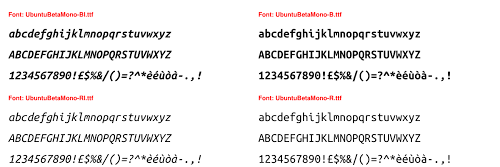
Ubuntu Font Family: Arriva il Font Ubuntu Monospace beta! Ecco come installarli su Ubuntu
Novità in casa Canonical, da pochi giorni è disponibile il nuovo font Ubuntu Monospace (in versione beta) che va ad aggiungersi ai caratteri già disponibili. I nuovi Font Ubuntu Monospace saranno integrati sopratutto per l’utilizzo da terminale (come vedete dall’immagine sotto) completando quindo il nostro desktop con tutti i font Ubuntu.